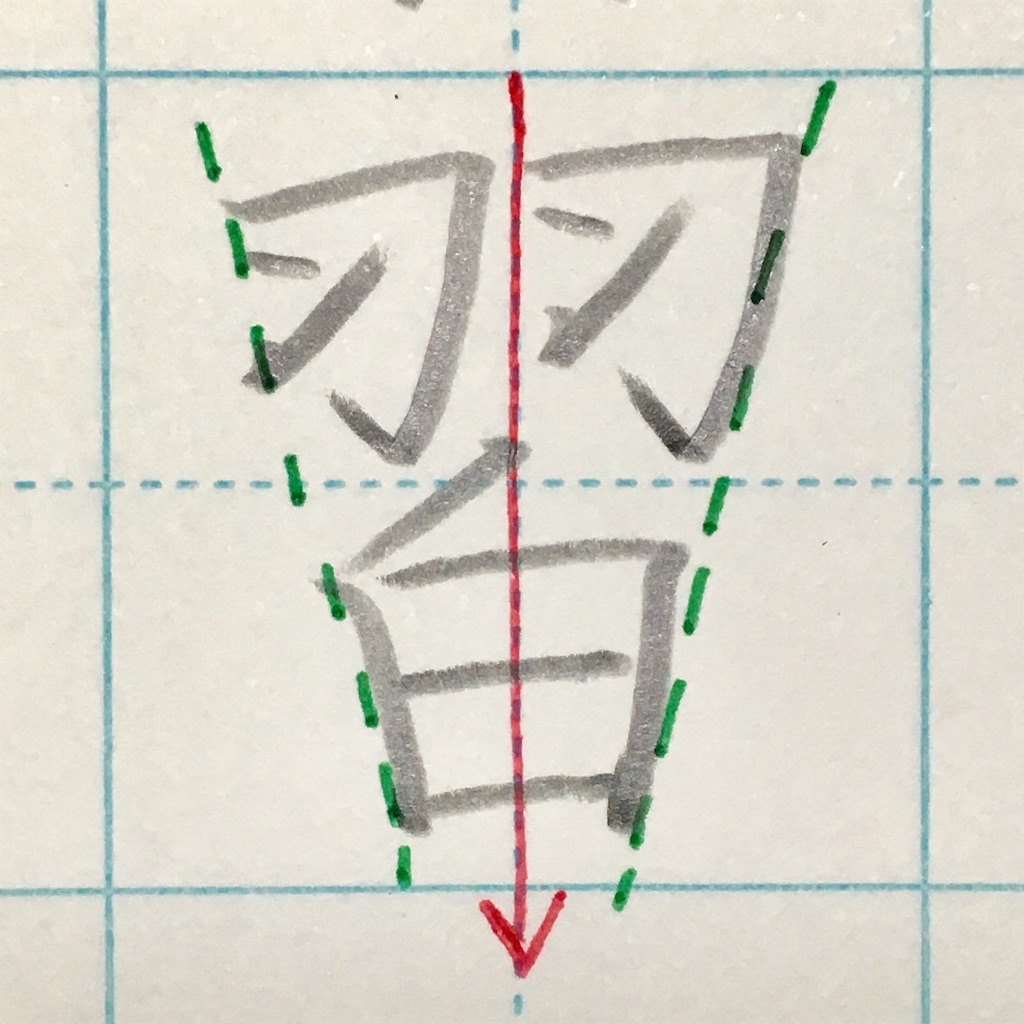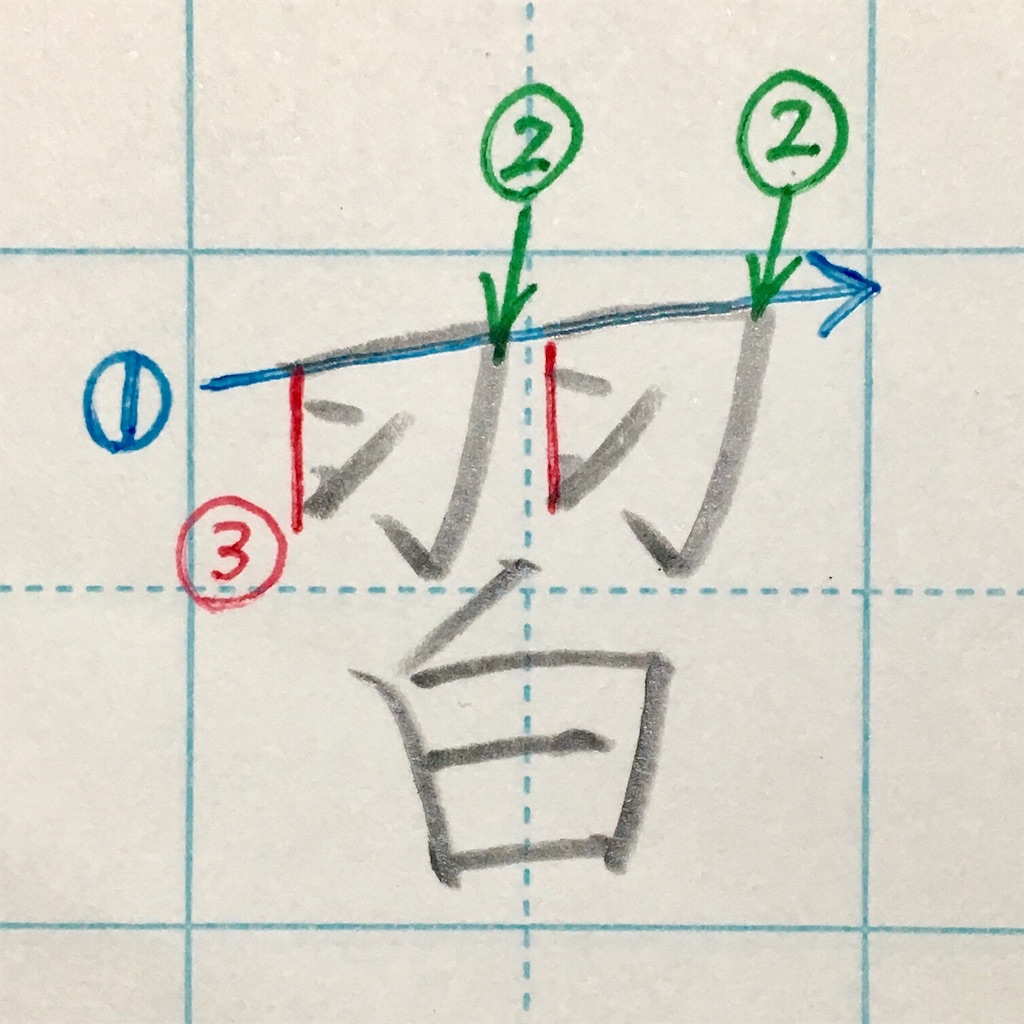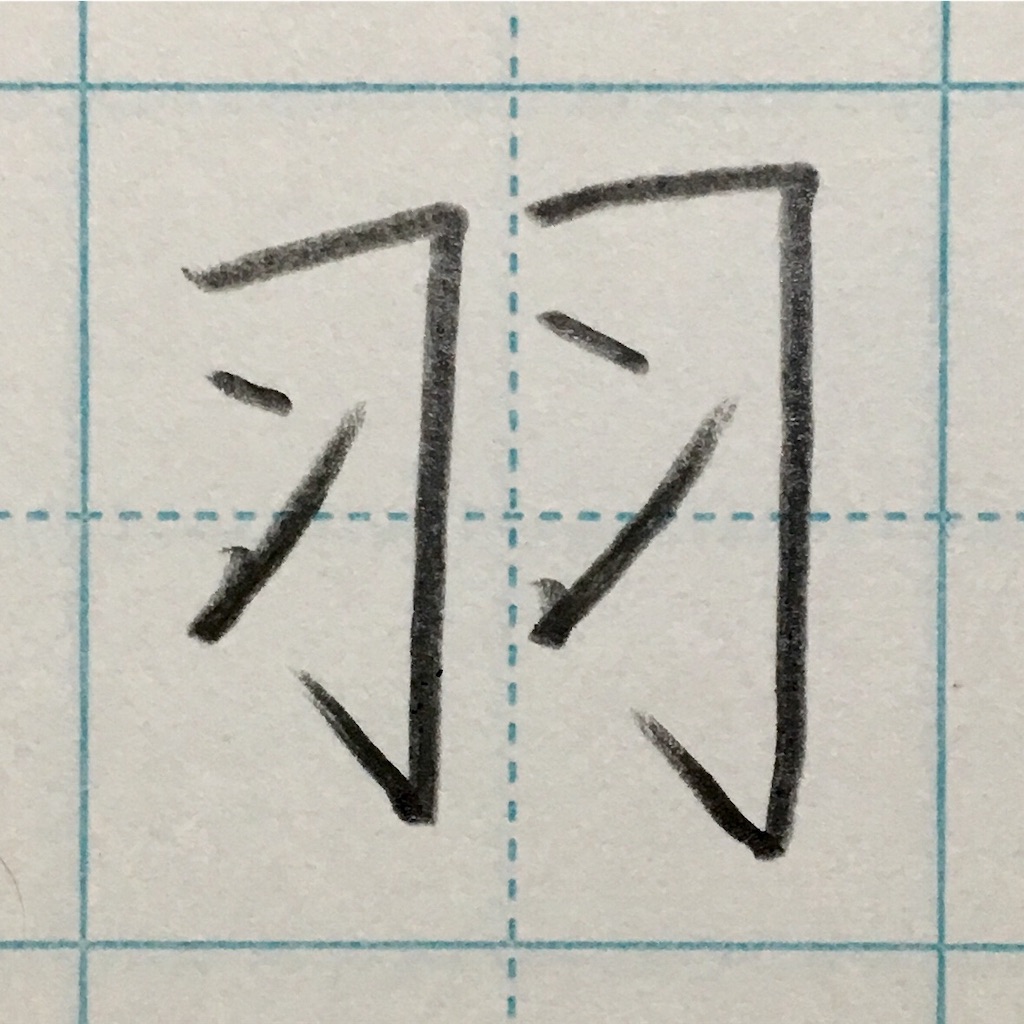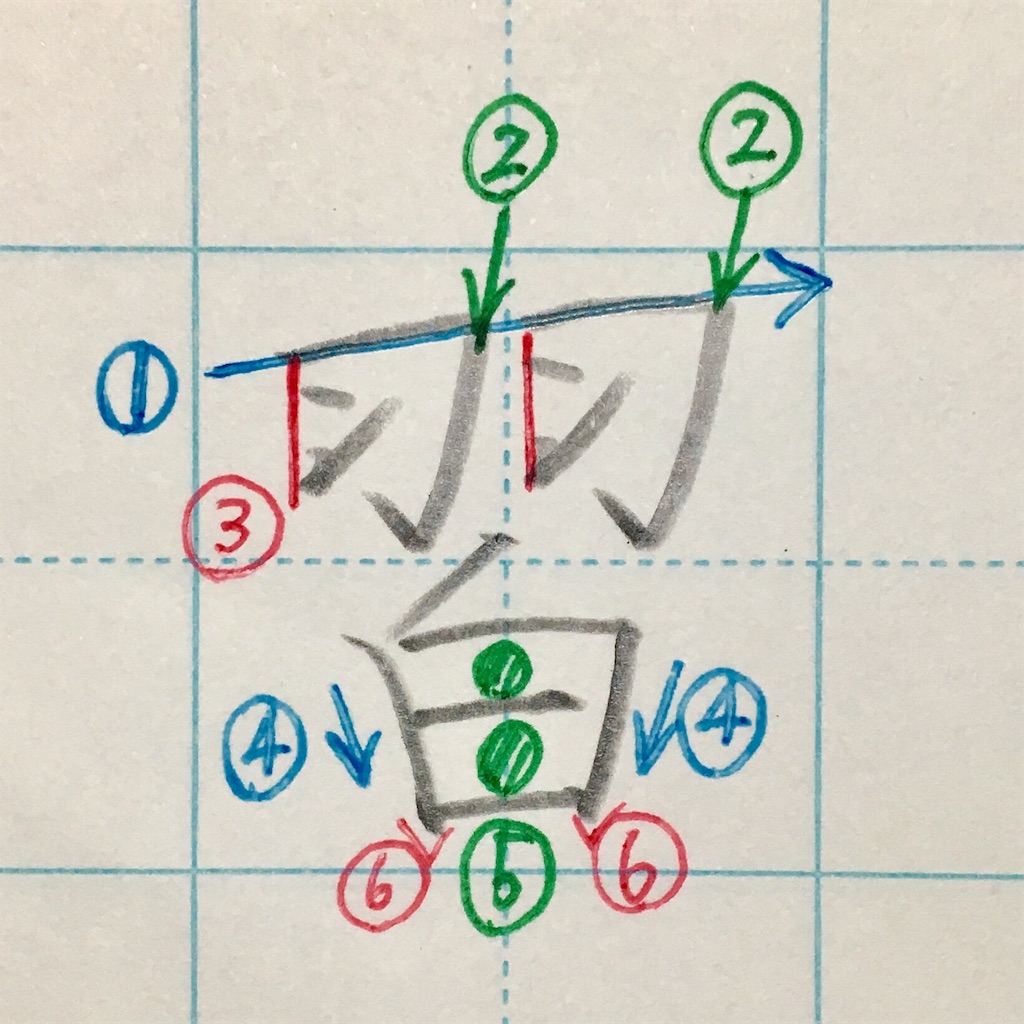
今回は「習」の書き方を解説します。
「習」のきれいな書き方
「習」の重要ポイント
☆まずは、中心を通す。
「羽」の真ん中のわずかな余白を確実に中心に持ってくる。
「白」は中心からスタート。
☆左右のラインを同じ角度で、だんだん狭くなるように意識する。
これができると、ガタつかず均整の取れた字になります。